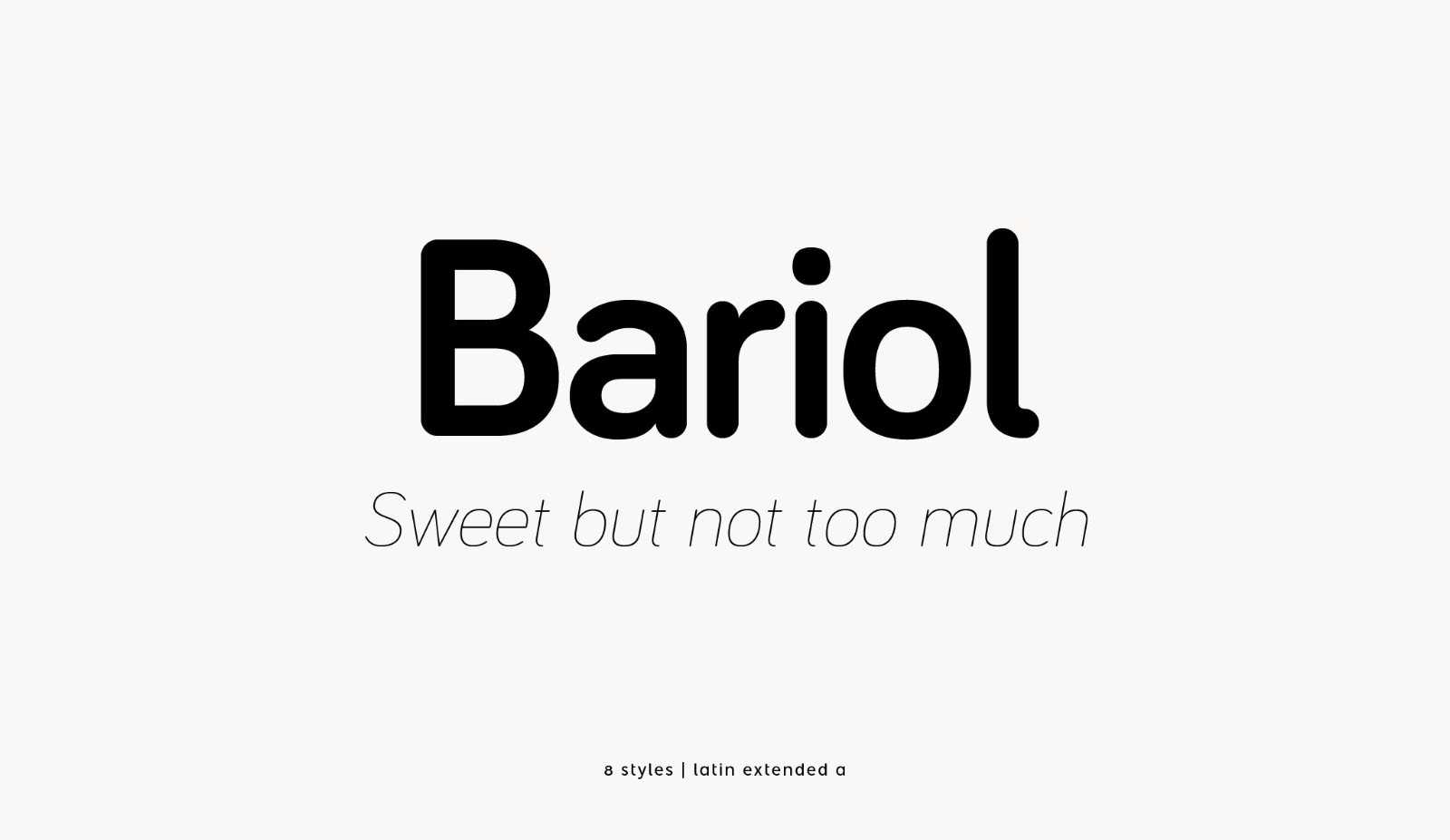
Bariol Condensed Rounded Font – Download Grátis
Bariol Condensed Rounded é uma fonte de design altamente versátil que atinge designers em todo o Brasil e mundo afora. Ela foi criada com um olho voltado para a leitura e para a versatilidade, adaptando-se facilmente tanto em projetos de design corporativo quanto em elementos gráficos e editoriais. Este estilo de fonte, que é um pouco mais comprimida e com contornos, mantém sua legibilidade mesmo quando aplicada em esquemas de tamanho reduzido. Seja em uma embalagem de produto, uma ilustração interativa de infográficos, ou um design editorial, Bariol Condensed Rounded é uma opção perfeita para qualquer projeto. Seu estilo destaca-se de forma elegante e moderna, garantindo um visual atraente em qualquer aplicação.